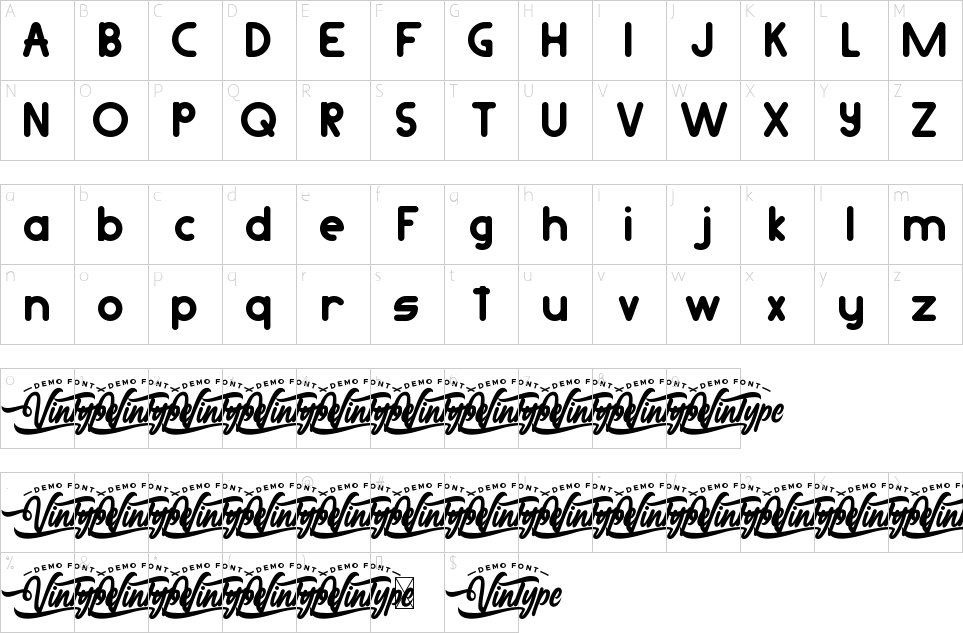
A fonte Metamora é uma opção gráfica agradável e de fácil leitura, especialmente adequada para aplicações que exigem um toque de sofisticação. Ela foi projetada pelo designer desconhecido vintype, e seu estilo minimalista e moderno contrasta bem com diversas mídias, como sites, aplicativos e materiais de marketing. Metamora foi baixada mais de 3.466 vezes, evidenciando seu valor como uma fonte versátil e de alta qualidade. Seja para criar um site elegante ou produzir materiais de marketing, Metamora oferece um visual moderno e harmonioso que certamente impressionará seus usuários. Se você está procurando por uma fonte versátil e elegante, esta pode ser uma excelente escolha.